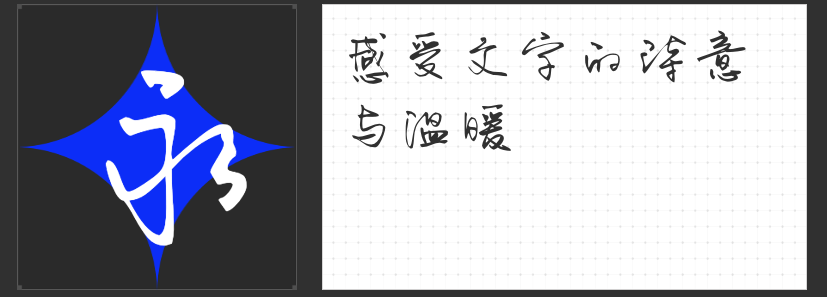
小豆岛字体推荐:感受文字的魅力与情感
在众多的字体中,小豆岛品牌的字体总能以其独特的韵味和风格吸引我们的目光。今天为大家推荐四款小豆岛品牌的字体,它们不仅各具特色,还能让你在书写中感受到不同的情感和意境。
首先推荐的是“小豆岛默陌枝桠简”。这款字体疏密有致,挥洒轻重缓急,仿佛让人置身于一幅传统的水墨画中。它既有传统书法的写意,又通过运笔节奏塑造出线条粗细和节点,呈现出一种枯枝藤蔓的造型感。使用这款字体,仿佛能表达出你潇洒肆意的个性,让人眼前一亮。
接下来是“小豆岛默陌乐童简”。这款字体上松下紧,笔画简单稚拙,充分体现出孩童的书写特点。它让人想起纯真的童年时光,那份无忧无虑、天真烂漫的感觉油然而生。选择这款字体,就像是在向内心深处的童心致敬,让文字也充满了童趣和梦想。
再来说说“小豆岛默陌纸鸢草书简”。这款字体连笔流连贯穿,笔画流畅恣意,气韵舒展潇洒。字体中宫更大,笔画更粗,不仅增强了字体的辨识度,还提高了其实用性。使用这款字体书写,就像是在纸上放飞一只纸鸢,让文字随风飘扬,传递出无尽的诗意与温暖。
最后是“小豆岛默陌写意水墨简”。这款字体清雅含蓄,既有传统书法的写意,又融入了现代手写的俏皮。笔尾锋芒毕露,笔触潇洒自如,线条富有节奏与灵气。它的水墨特点让文字仿佛有了生命,点缀其间,生动而富有情趣。
这四款小豆岛字体各具特色,无论是想要表达潇洒肆意的个性、纯真无邪的童心、诗意温暖的情怀,还是清雅含蓄的气质,都能在这些字体中找到共鸣。快来试试这些字体吧,让文字成为你表达情感与个性的独特方式。